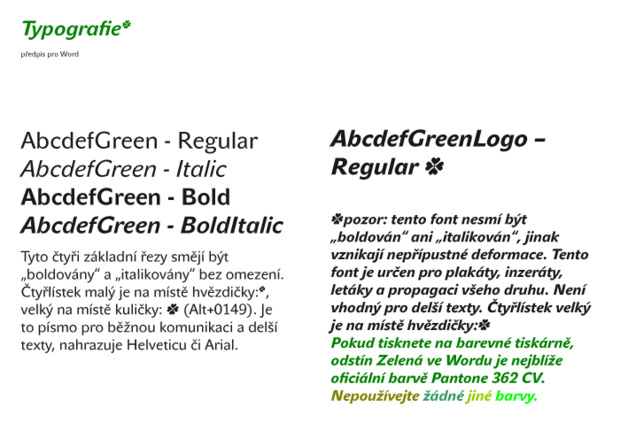
Kosten- und serifenlose Schrift zur Mercury?
fällt Euch ad hoc eine schöne kosten- und serifenlose Schrift ein, die gut zur Mercury passt?
Hm ... Wofür denn? Solls sich anschmiegen oder kontrastieren? Weil, so richtig viele altmodische kostenfreie Serifenlose wirds nicht geben ... Die Liberation ist etwas altmodischer und hat vielleicht ne annähernd hohe x-Höhe ... Musst Du mal Probefahren, aber zumindest das M hat auch nen Mittelteil bis zur Grundlinie ... :-?
Wie soll denn die Anmutung sein? Spontan sehe ich gerade die Mercury (H & F.-J. nehme ich an?) immer mit einer schmal laufenden Serifenlosen wie z.B. der hauseigenen (und wunderschönen) Tungsten. Wenn es in diesem Fall kostenlos sein soll, dann käme natürlich ggf. die PT Sans Narrow in Frage oder die Alternate Gothic No 2 von E + F.
Wenn es 20 Euro kosten darf: wie wäre es mit der fetten Azuro? Ich habe die Mercury nicht und kann die Kombination nicht ausprobieren, aber die fette Azuro gefällt mir ja für Überschriften ganz gut, wenn ich die ganze Familie auch für’s Lesen am Bildschirm ziemlich ungeeignet finde ...
Oder soll es ganz anders aussehen? :-?
Ich habe ein Corporate Design für eine Kleinkundin entwickelt, bei dem ich die Mercury für das Logo und den Text auf Visitenkarte und Briefbogen eingesetzt habe. Dazu schön kontrastierend benötige ich nun eine Fließtextschrift, die sie für ihre Kommunikation einsetzen kann. Da das Budget nicht riesig ist, ich aber vermeiden möchte, dass sie in ihrer Not auf die Arial zurückgreift, habe ich gedacht, ich schaue mich mal nach einer brauchbaren kostenlosen Variante um. Geplant ist als nächster Step durchaus die Anschaffung einer Schrift – aber bis das Budget das hergibt brauchen wir eine Zwischenlösung … :-?
Gotham wäre eine Suggestion …
Nicht ganz kostenfrei, sicherlich, aber vielleicht hast du sie ja eh schon … :-)
Ich habe sie – aber meine Kundin leider nicht. :-) Und die Gotham kannst Du nur im Paket kaufen – da haut der Preis dann gleich mächtig rein. Mal ganz davon abgesehen, dass meine Kundin maximal zwei Schnitte benötigen würde und das Paket daher ziemlich verschwendet wäre … Aber die Gotham ist ansonsten natürlich sehr schön und auch die Whitney passt wunderbar zur Mercury. Und beide sprengen leider absolut den Kostenrahmen … :cry:
… Fließtextschrift …
Ah, na dann geht es natürlich eher nicht mit einer condensed. Ich hatte mir das gerade andersherum vorgestellt. Da muß dann ja was sehr lesbares her. Wie wäre es mit der ABCGreen von Herrn Štorm? Obwohl, die sind vermutlich beide zu eigenwillig um wirklich zueinander zu passen. Lesen läßt sich die aber ganz gut und umsonst ist sie auch! ;-)
Ah, na dann geht es natürlich eher nicht mit einer condensed. …
Und wenn wir die PT Sans als fast condensed bezeichnen? ;-)
»fast« Deutsch oder Englisch? :lol:
Aber mal im Ernst: findest Du die PT Sans als Fließtextschrift gut geeignet? Insbesondere wenn die Dame die Mercury als Logo-Font hat? Ich fand die PT Sans bisher für Überschriften super, im Fließtext ist sie mir zumindest über längere Strecken irgendwie nicht lesbar genug. Oder widersprichst Du mir da vehement?
… Oder widersprichst Du mir da vehement?
Überhaupt nicht :-) Für Geschäftspost sollte sie aber gehen.
Ralf hat da offenbar eine ganz trickreiche Erkennung in die Forensoftware integriert! Big Brother und so! Jetzt auch neu über Typografie.info! :nicken:
Wie wäre es mit der ABCGreen von Herrn Štorm
Ich glaube ich stelle mich gerade echt blöd an, aber ich finde die Schrift nicht … Verrätst Du mir, wo ich sie anschauen kann? :oops:
Ich habe meiner Kundin jetzt mal die Liberation und die PT Sans gezeigt, mal sehen, was sie sagt … Und wenn ich es gebacken kriege mir die ABCGreen anzuschauen, dann zeige ich ihr die auch noch. Lieben Dank für Eure Hilfe! :biglove:
Huch? Ich bin mir absolut sicher daß Herr Štorm die vor einiger Zeit frei zum Download angeboten hat (daher habe ich sie selber)! Wenn Du hier schaust kannst Du noch Bilder bewundern (und verifizieren daß sie wohl kaum zur Mercury paßt?!). Falls sie wider Erwarten doch interessant sein sollte würde ich ggf. mal Herrn Štorm direkt kontaktieren. Der war mir gegenüber immer so furchtbar nett und zuvorkommend. :biglove:
Im Archiv hab ich noch was gefunden:
Wobei ja zur Einschätzung dieses Bild noch aussagekräftiger wäre:
Ist schon ziemlich typisch für Herrn Štorm. Sie läßt sich aber in Fließtexten ziemlich gut lesen, und das auch in recht kleinen Schriftgraden, ähnlich wie die Anselm Sans auch.
@ bertel: Dankeschön :-D Darauf hatte Christian auch verlinkt … neben der schönen Schrift finde ich auch die Erläuterung bemerkenswert, die Herr Štorm unter die Beispiele geschrieben hat …